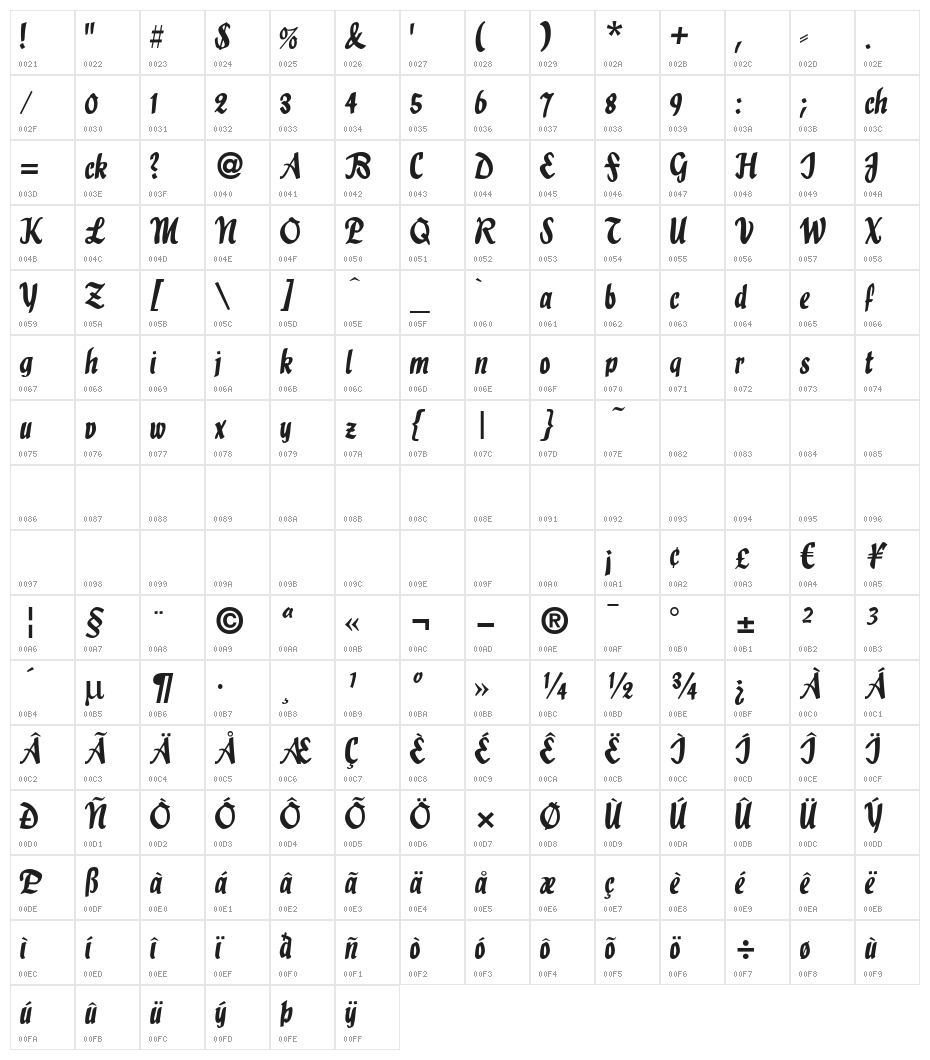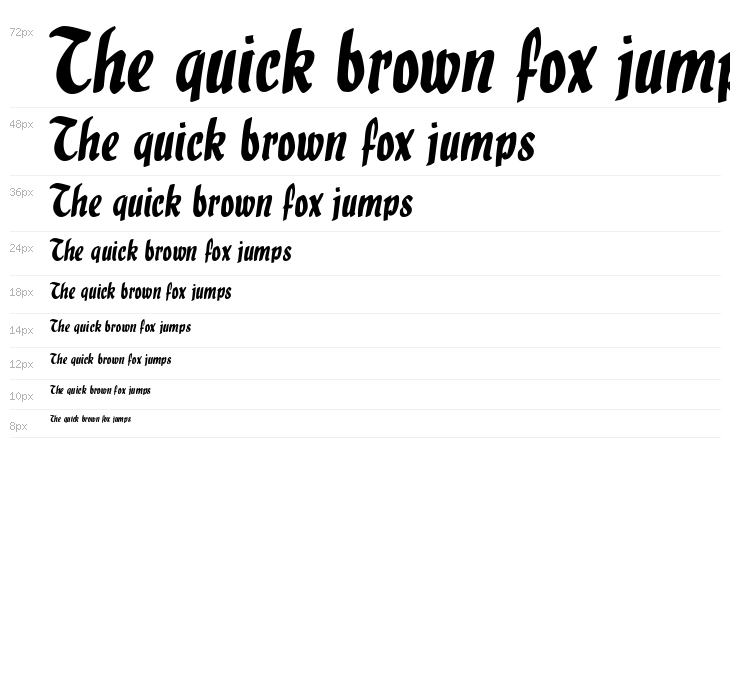
Holla Font
✎ Calligraphic
| Anwendungsfall | Logos, Headlines, Invitations |
| Vorgeschlagene Projekte | Ideal for wedding invitations, branding, logos, and elegant packaging designs. |